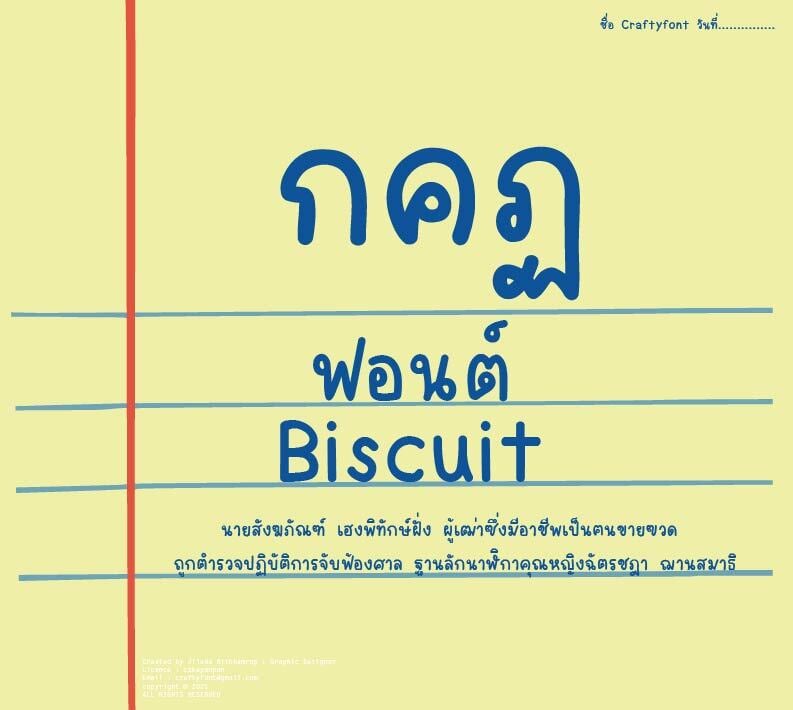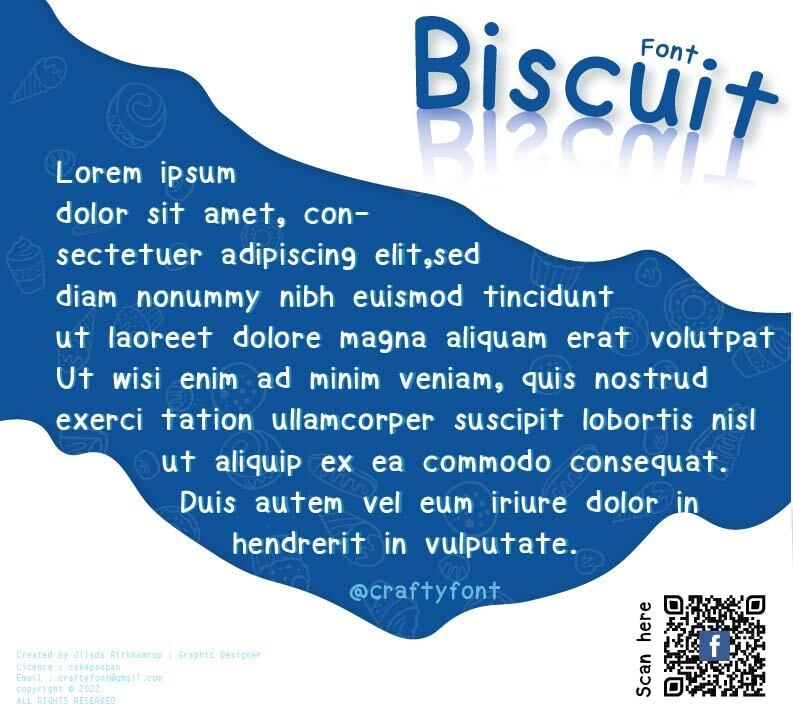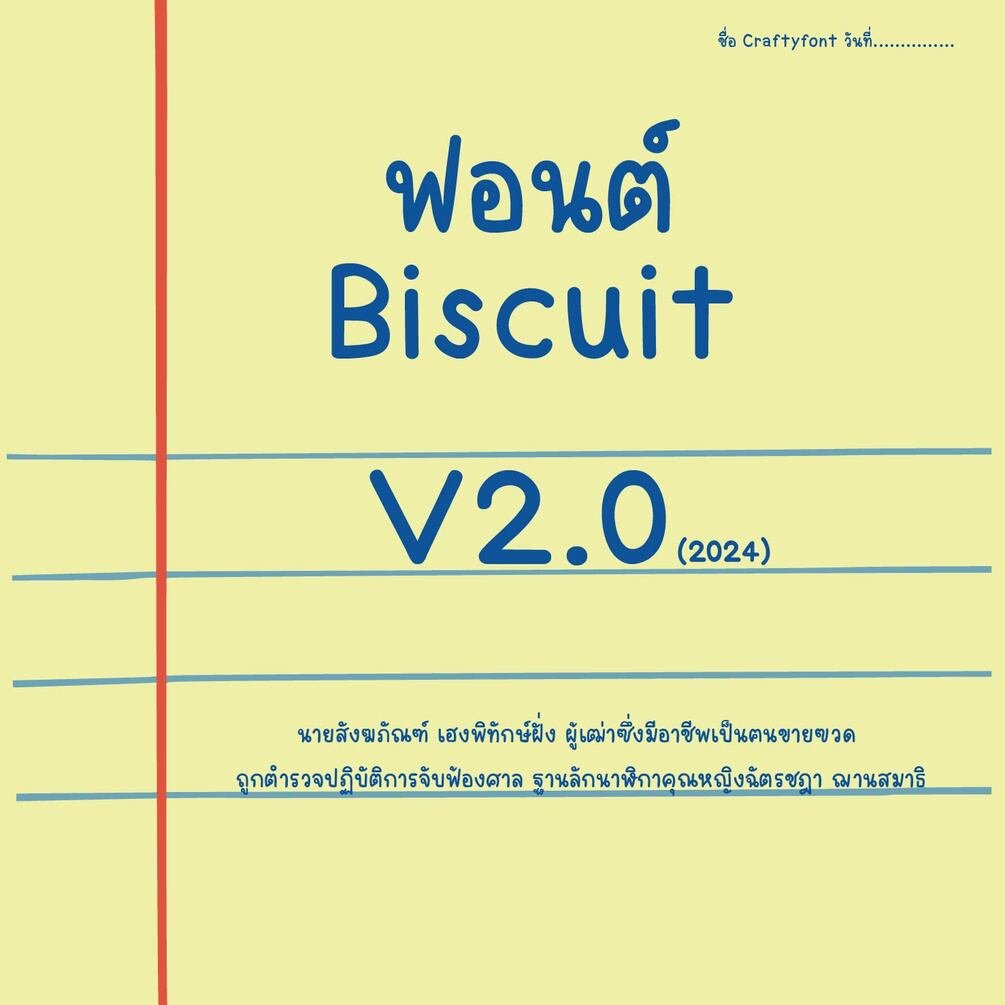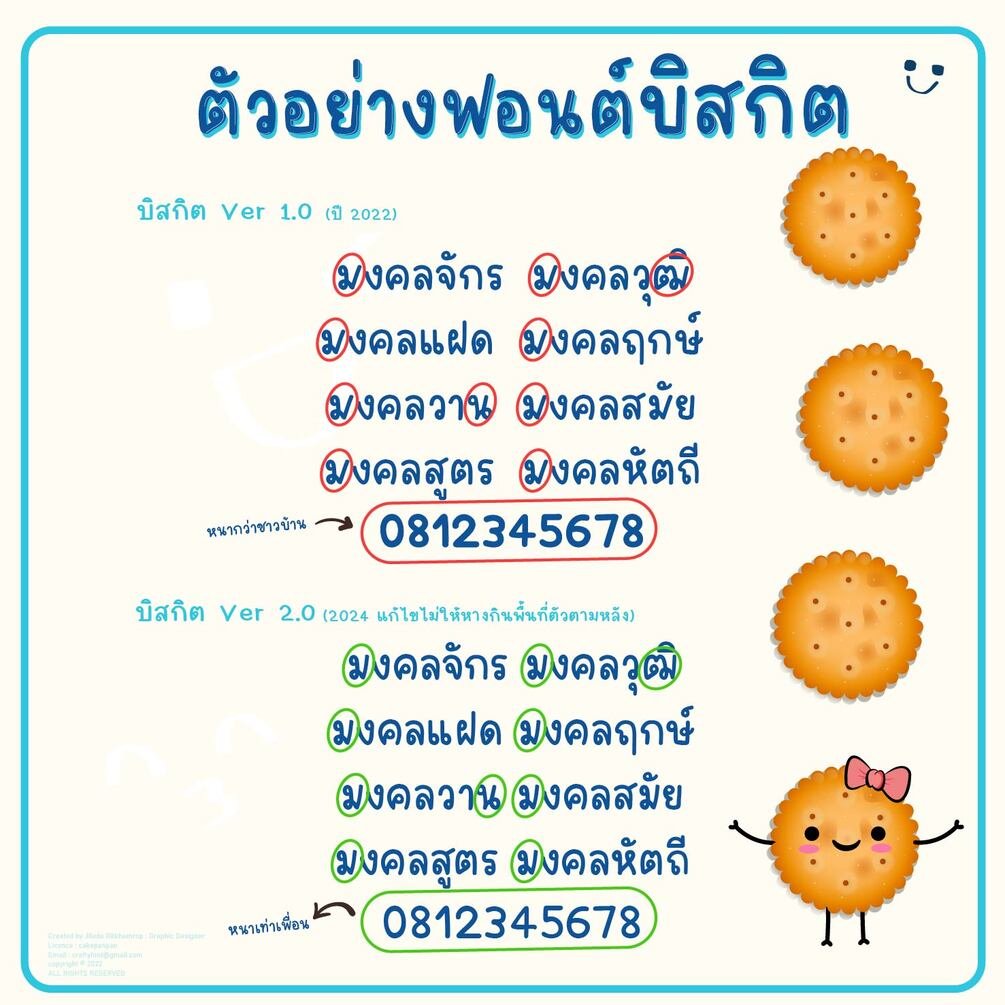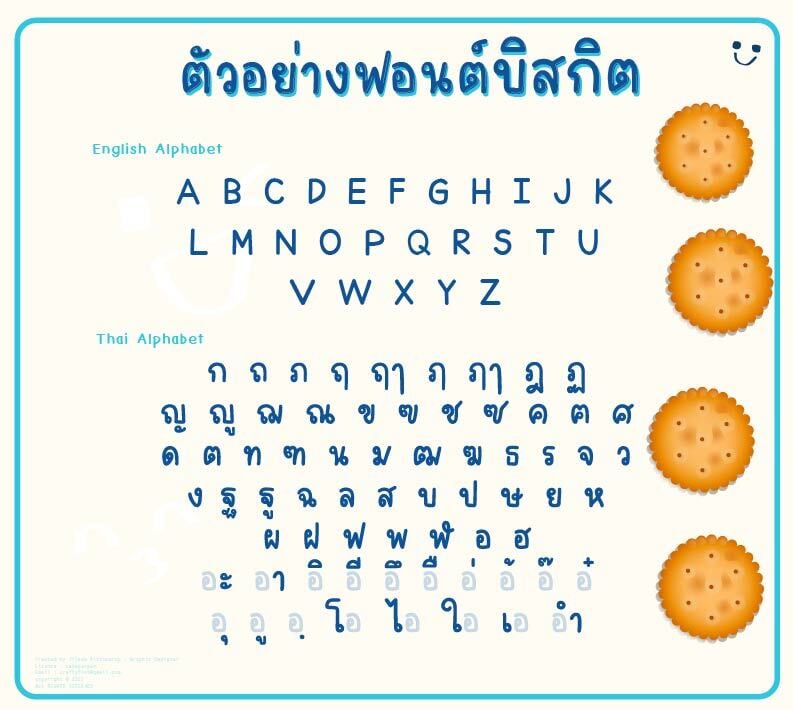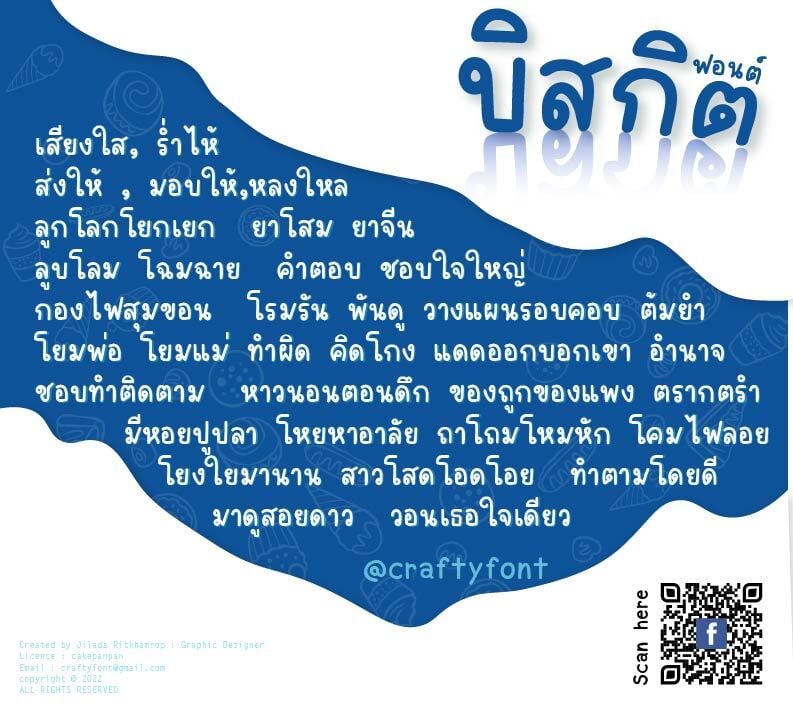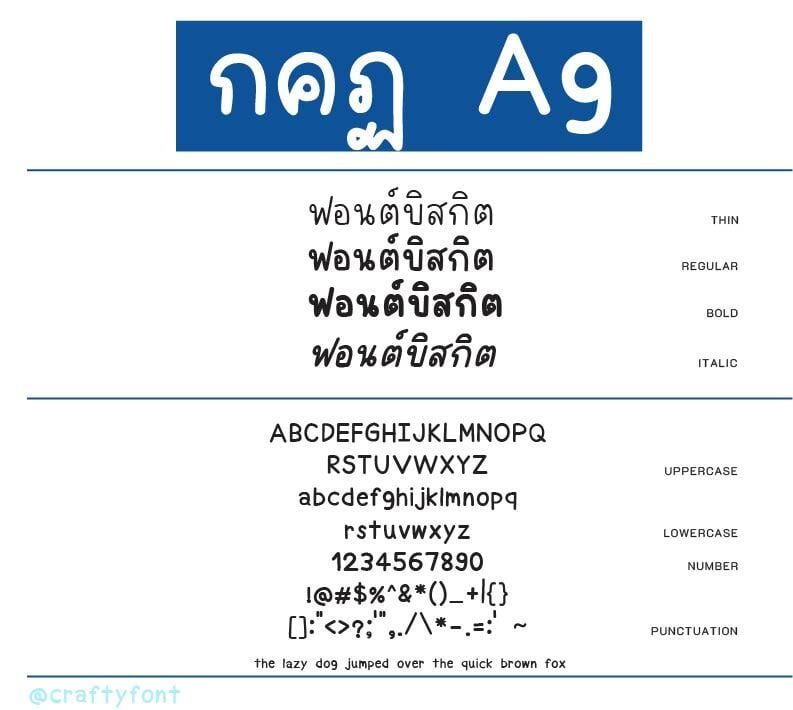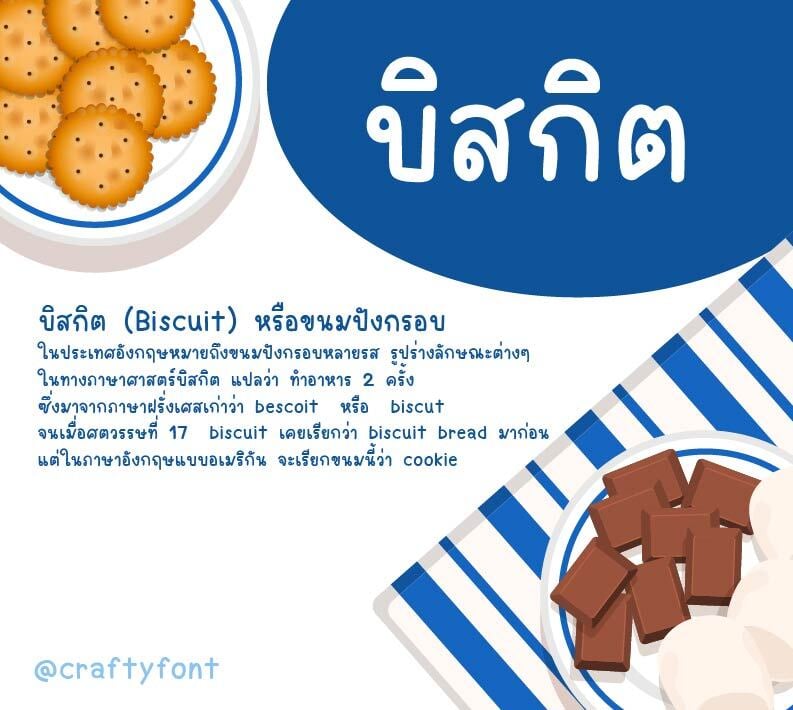
Biscuit Font (ฟอนต์บิสกิต)
2022 ฟอนต์บิสกิตเวอร์ชั่น 1.0
2024 ฟอนต์บิสกิตอัพเดตเวอร์ชั่น 2.0 แล้ว! สามารถใช้งานบนแอพ Capcut ได้!🍪
ฟอนต์บิสกิตออกมาได้ 2 ปีแล้วค่ะ เมื่อมีนา ปี 2022 ปัจจุบันยังคงมีคนดาวโหลดไปใช้งานอยู่ และมีหลายคนได้แจ้งปัญหาเข้ามา แพนจึงได้รวบรวมแล้วอัพเดตฟอนต์เป็นเวอร์ชั่น 2.0 ที่ Fix หลายๆ ปัญหา ทั้งเรื่องหางม.ม้า ฒ.เฒ่า และ น. หนู ที่ทะแยงมากเกินไป แก้ระยะห่างระหว่างบรรทัด แก้ตัวเลขที่หนาเกินตัวอักษร และที่สำคัญสามารถใช้ฟอนต์บิสกิตบนแอพ capcut โดยที่สระและวรรณยุกต์ไม่เพี้ยนได้แล้วด้วย!
ฟอนต์บิสกิตมีทั้งภาษาไทยและภาษาอังกฤษเลยนะคะ แฟมิลี่เซ็ตนี้มี 3 ขนาดด้วยกัน ทั้งตัวหนา ตัวเอียง และตัวปกติ สัญลักษณ์บวกลบคูณหารมีให้ใช้ครบ ฝากไว้ในอ้อมอกอ้อมใจพี่จ๋าด้วยนะจ๊ะ 🥰